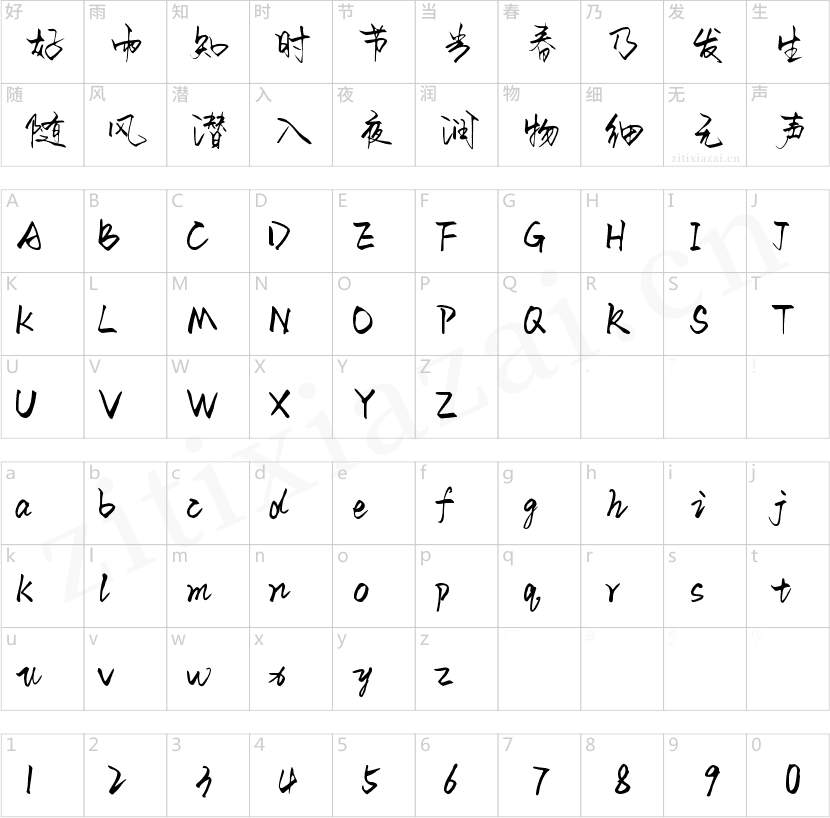
Aa星河依旧滚烫
Aa星河依旧滚烫字体
Aa星河依旧滚烫是一款非常具有艺术性的字体,它的设计灵感来源于对古典艺术的研究,同时又融入了现代字体设计的元素。字形优美,笔画粗细变化自然,给人以大气、典雅的感觉。Aa星河依旧滚烫是一款既传统又现代的字体,它的设计充满艺术感,美观大方,实用性也非常强。无论是对于设计师还是对于普通读者来说,都是一种非常不错的字体选择。Aa星河依旧滚烫适合用于具有艺术感的场合,比如海报、宣传单张、书籍封面等。由于其字形流畅且具有动态感,也适合用于大量的文本排版,如报纸、杂志等。